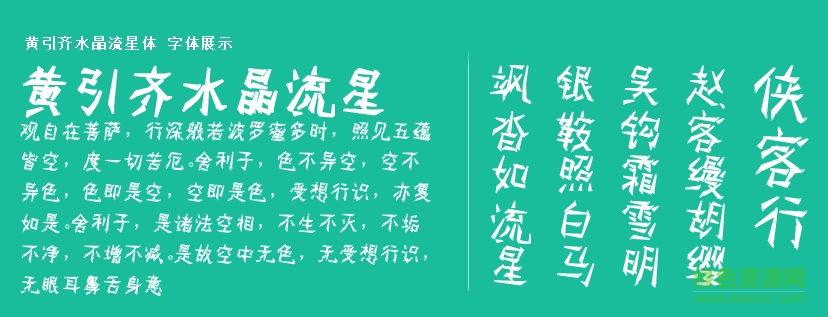
黃引齊水晶流星字體
黃引齊水晶流星是黃引齊字庫(kù)新推出的美工字體,微斜的字體邢臺(tái)給人流動(dòng)的而徐緩的舒適體驗(yàn),讓圖片、廣告等圖文更顯活潑生動(dòng),歡迎大家來(lái)綠色資源網(wǎng)體驗(yàn)!
黃引齊水晶流星字體介紹
黃引齊水晶流星,創(chuàng)意靈感來(lái)源于經(jīng)典網(wǎng)絡(luò)游戲《奇跡》中曾經(jīng)的神器:水晶流星!
黃引齊水晶流星